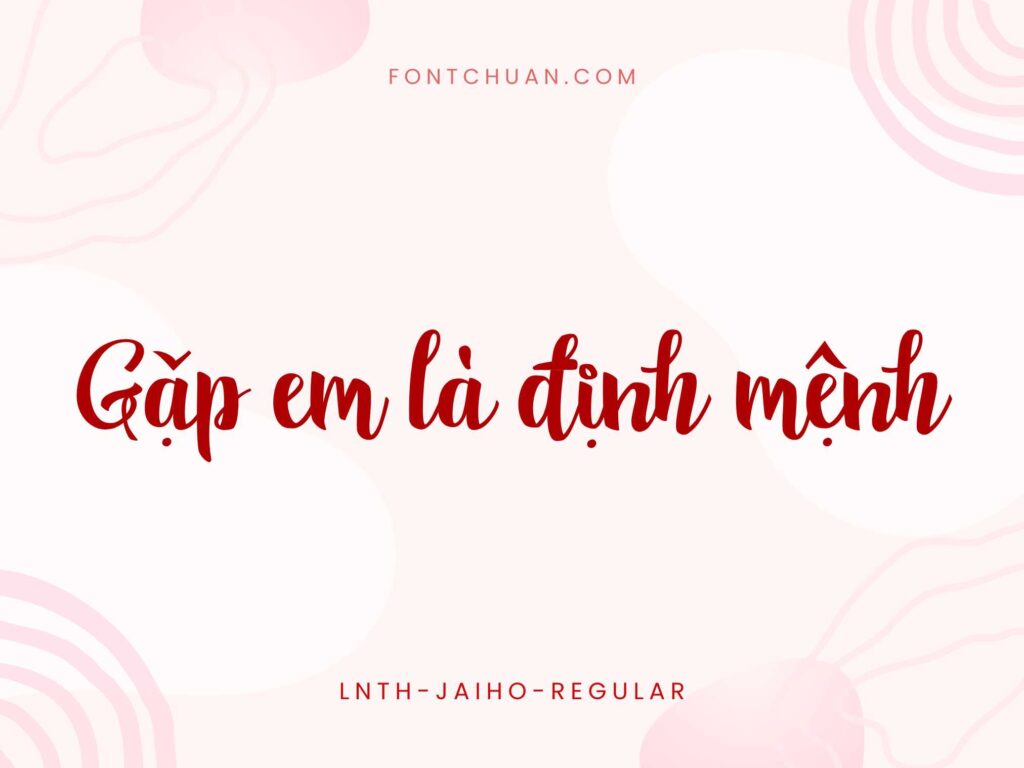
Font LNTH Jaiho Script Việt Hóa
Jaiho là một phông chữ viết tay độc đáo, mang phong cách hiện đại và sáng tạo. Phông chữ này kết hợp giữa sự mềm mại của chữ viết tay và sự mạnh mẽ của nét cọ, tạo nên sự cân bằng hoàn hảo cho các thiết kế cần sự nổi bật và thu hút. Nhờ được Việt hóa bởi LNTH, Jaiho hỗ trợ đầy đủ các ký tự tiếng Việt, giúp người dùng dễ dàng áp dụng trong các dự án đa ngôn ngữ. Phông chữ này đã được sưu tầm và đăng tải bởi thành viên của Font Chuẩn, đáp ứng nhu cầu đa dạng của cộng đồng thiết kế.
Về đặc điểm thiết kế, Jaiho sở hữu các ký tự được vẽ tỉ mỉ với những đường nét uyển chuyển và tinh tế, mang lại cảm giác thân thiện và gần gũi. Phông chữ này đặc biệt phù hợp cho các dự án như thiết kế logo, bìa sách, poster, thiệp mời và các ấn phẩm quảng cáo, nơi cần sự sáng tạo và độc đáo. Ngoài ra, Jaiho cũng thích hợp cho các sự kiện như lễ hội, sinh nhật, Valentine và Trung thu, mang lại không khí ấm áp và vui tươi. Trong lĩnh vực ngành nghề, phông chữ này được ứng dụng rộng rãi trong quảng cáo, thiết kế thiệp cưới, giáo dục và công nghệ, góp phần tạo nên sự thu hút và chuyên nghiệp cho các sản phẩm và thương hiệu.